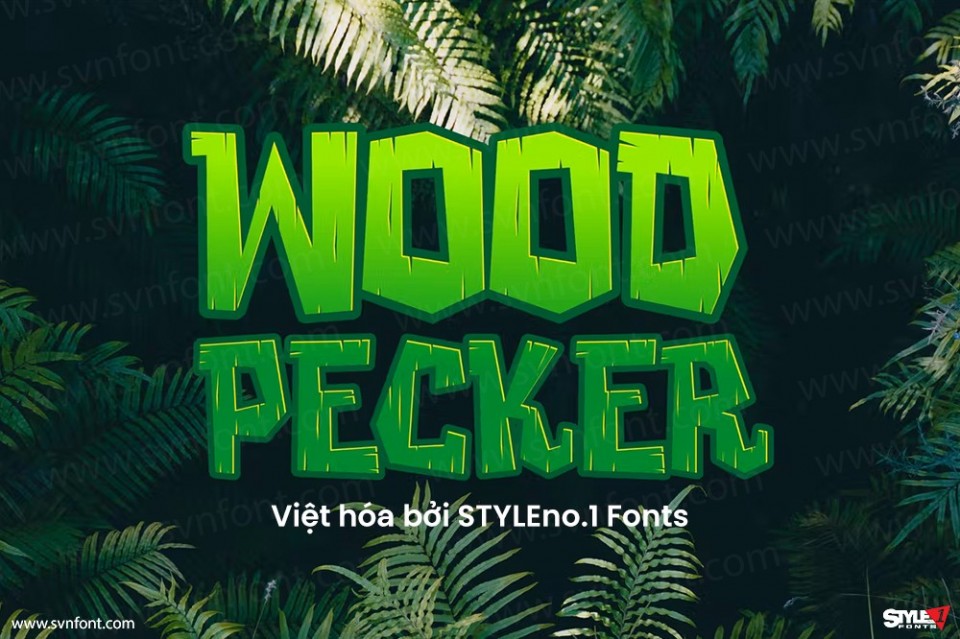
Font việt hóa SVN Woodpecker
Giới thiệu về Font việt hóa SVN Woodpecker
Trong cộng đồng thiết kế đồ họa tại Việt Nam, việc tìm kiếm một bộ Font Miễn Phí chất lượng luôn là ưu tiên hàng đầu. Font việt hóa SVN Woodpecker nổi lên như một lựa chọn hoàn hảo dành cho những ai yêu thích phong cách mộc mạc và gần gũi. Đây là bộ phông chữ được tinh chỉnh kỹ lưỡng về dấu tiếng Việt, giúp các bạn học sinh và giáo viên dễ dàng ứng dụng vào các bài thuyết trình hay dự án học tập mà không lo lỗi hiển thị. Với các đường nét mô phỏng nét khắc gỗ thủ công, bộ font này mang lại cảm giác ấm áp, tự nhiên và vô cùng ấn tượng.
Đặc điểm nổi bật của Font việt hóa SVN Woodpecker
Phong cách thiết kế độc đáo
Font việt hóa SVN Woodpecker sở hữu cấu trúc chữ cái vững chãi nhưng không kém phần mềm mại. Các nét vẽ không quá trau chuốt giúp tạo nên vẻ ngoài cổ điển, phù hợp cho các bìa sách giáo khoa, áp phích sự kiện trường học hoặc các thiệp mời handmade. Sự linh hoạt của nó giúp người dùng dễ dàng kết hợp với nhiều loại hình ảnh khác nhau từ hiện đại đến truyền thống.
Khả năng ứng dụng đa dạng
Không chỉ dừng lại ở các ấn phẩm in ấn, bộ font này còn hoạt động cực kỳ tốt trên các nền tảng kỹ thuật số. Nhờ bảng mã chuẩn, bạn có thể sử dụng nó trong các phần mềm phổ biến như Photoshop, Illustrator hay thậm chí là Microsoft Word để soạn thảo văn bản. Tính ứng dụng cao giúp sản phẩm luôn nằm trong danh